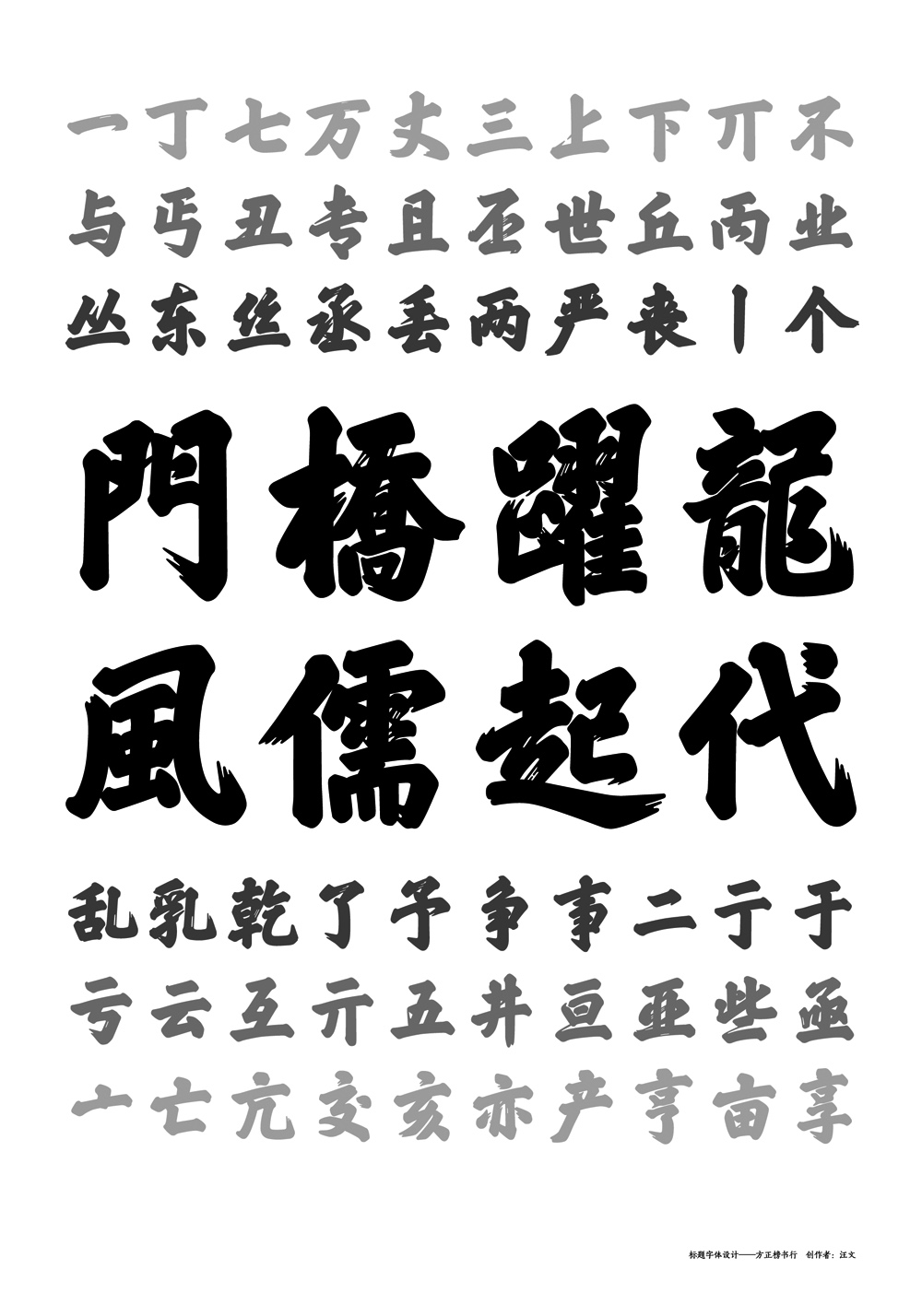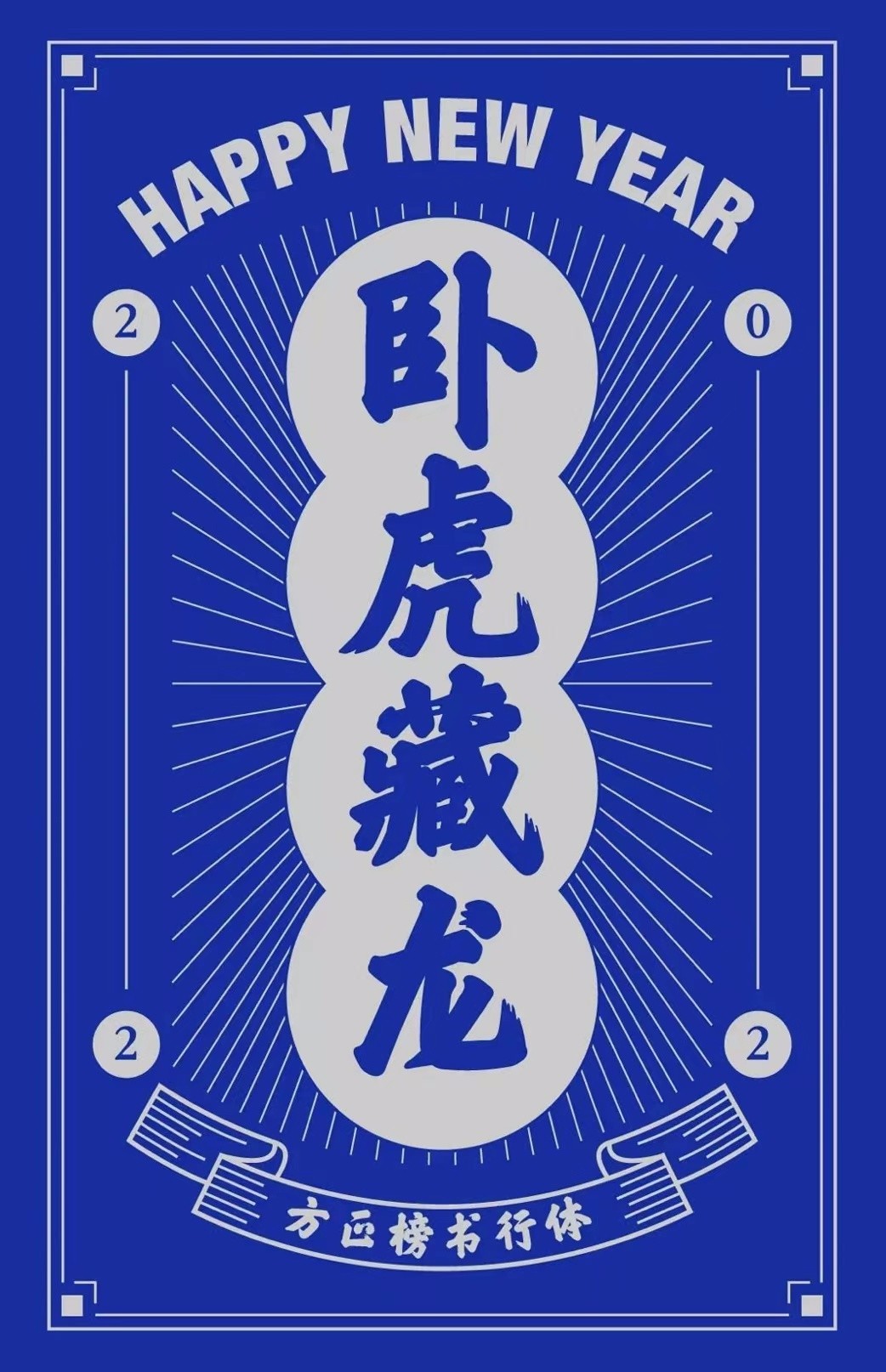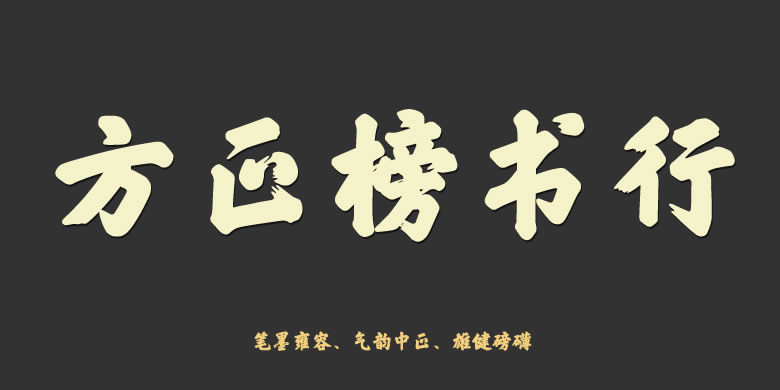
方正榜书行
字体品牌: 方正字库 设计师:汪文 字体分类:行楷、行书、创意字体 字体属性:精品字 字符集:大陆简体(GB2312-80)、简繁扩展(GBK) 发布时间: 2014
方正榜书行的设计源于明、清两朝宫阙匾额、楹联上的行楷大字。榜书为历代书家所推崇,古人形容榜书:笔墨雍容,气韵中正,雄健磅礴,自古为难。方正榜书行将传统书法与现代字体设计相融合,保留了毛笔书写的笔触,増加了飞白处理,笔形追求笔墨的情趣,做到古为今用。这款字非常适用于各类具有传统习俗的包装和宣传设计,传递出浓烈的喜庆气氛。
方正榜书行排版展示效果
2014年,方正榜书行荣获美国CA“2014国际文字设计比赛”字体设计类CA传艺优异奖
2015年,方正榜书行荣获“2015中国设计红星奖 银奖”
方正榜书行创意展示
方正榜书行模拟应用效果